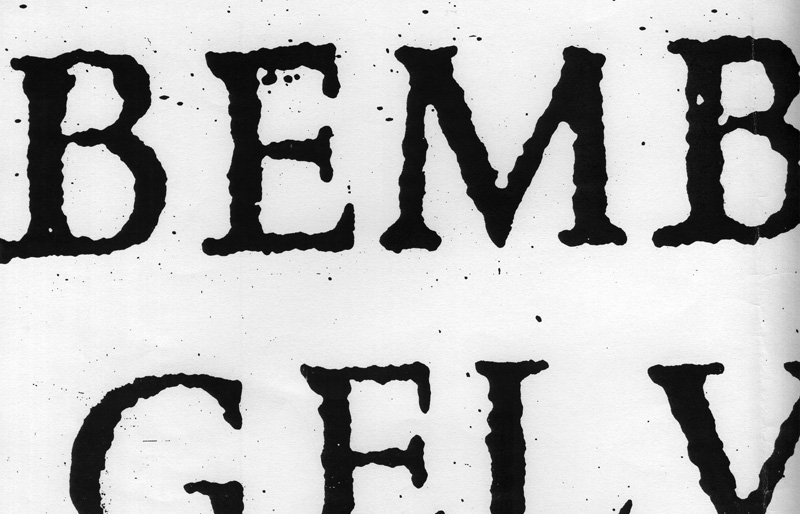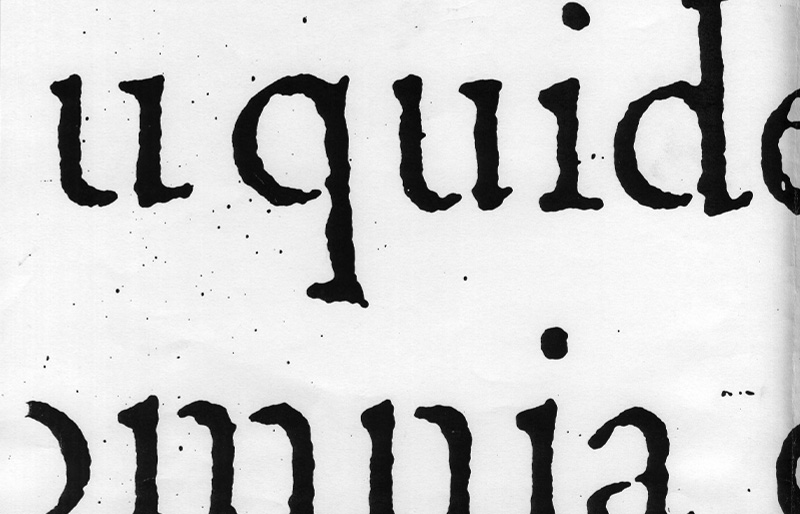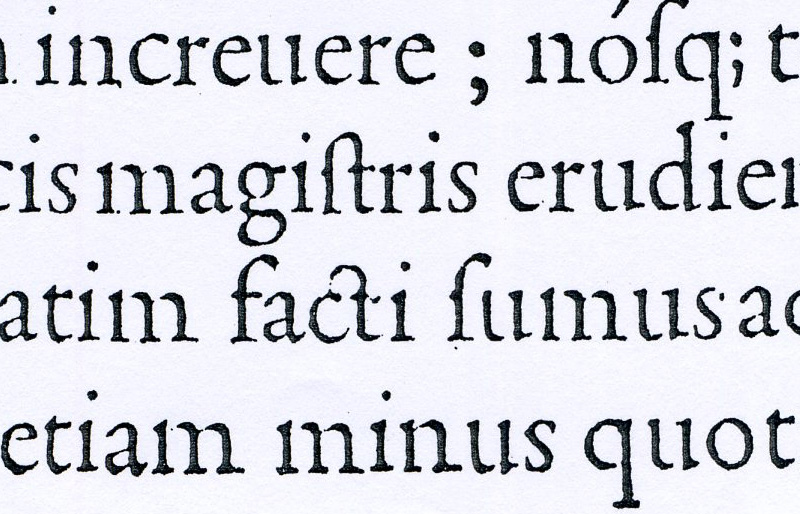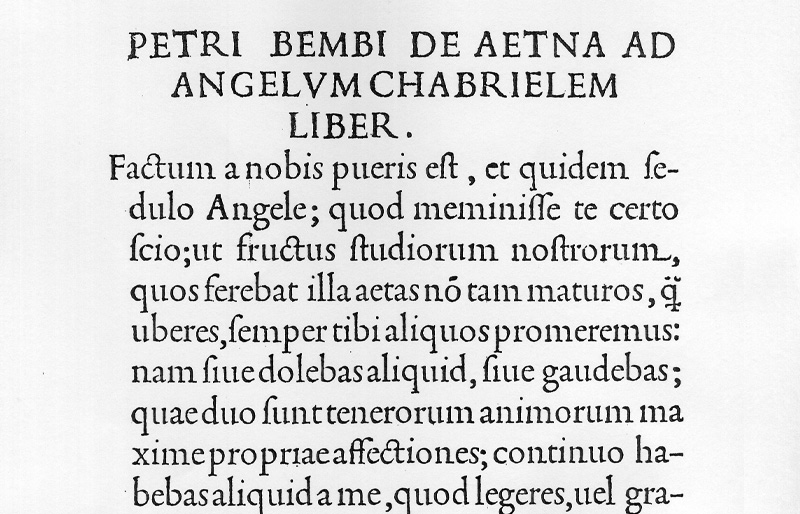
Understanding roman type
Pietro Bembo'nun1496'da Venedik'te Aldus Manutius tarafından basılan De Aetna adlı eseri için Francesco Griffo'nun işlediği Latin yazıbiçimine bakacağız. Bu yazıbiçimi detaylarını ve yapısını, modern harf karakterleri (Latin, serifsiz ve diğerleri) üretmek için nasıl yorumlanabileceğini anlamaya çalışacağız. Bunu yaparken tarihi Latin yazıbiçimini anlamak için en uygun araç olan 3B kurşun kalem kullanacağız. Çalışmamızın başlangıç noktası De Aetna'nın ilk baskısının büyütülmüş fotoğrafları olacak.